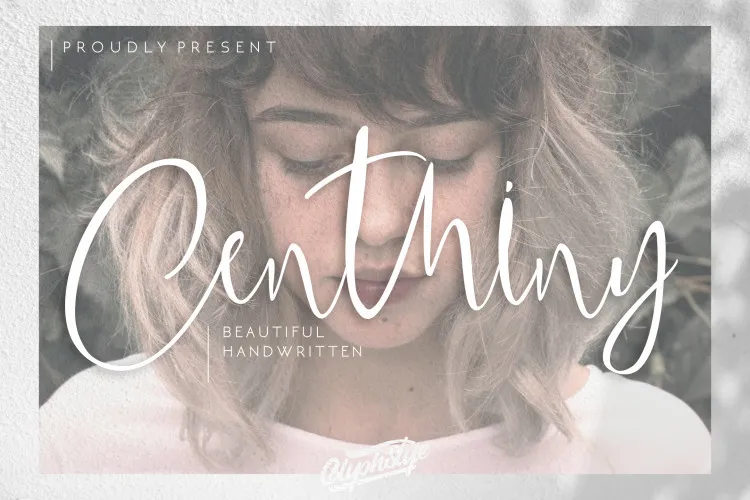
Centhiny Handwritten Font – Download Grátis
Olá pessoal, hoje apresentamos a vocês uma fonte feita à mão que é simples e bela, perfeita para uso múltiplo tanto em logotípicos quanto para escrever sobre sua empresa. Centhiny foi desenvolvida por GlyphStyle, designer famoso aqui na nossa comunidade digital. Esta fonte criada à mão pode transformar projetos de design em algo elegante e moderno, adaptando-se perfeitamente a uma variedade de usos, desde saudações de natal até convites para casamentos. Ela se encaixa perfeitamente em vários tipos de mídia social, blogs, logotipos, desenho de roupas, tipografia e muito mais. Descubra o verdadeiro valor desta fonte no seu próximo projeto criativo. Não deixe essa grata oportunidade passar! Centhiny é uma opção incrível para quem busca algo singular e elegante em sua próxima design.